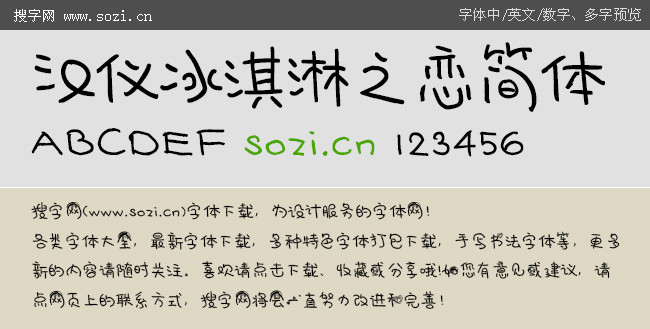
漢儀冰淇淋之戀
搜字網(wǎng)給大家提供一款漢儀冰淇淋之戀中文字體下載,漢儀冰淇淋之戀是一款卡通風(fēng)格中文字體。該字體的設(shè)計(jì)非常有特點(diǎn),字形筆畫(huà)的形狀就像是冰淇淋在融化一般,非常的可愛(ài),充滿(mǎn)了藝術(shù)感。適用于兒童畫(huà)冊(cè)設(shè)計(jì)、卡通海報(bào)設(shè)計(jì)、包裝設(shè)計(jì)等場(chǎng)合使用。(本字體為個(gè)人非商用版,如需要商用請(qǐng)聯(lián)系漢儀公司購(gòu)買(mǎi)版權(quán))